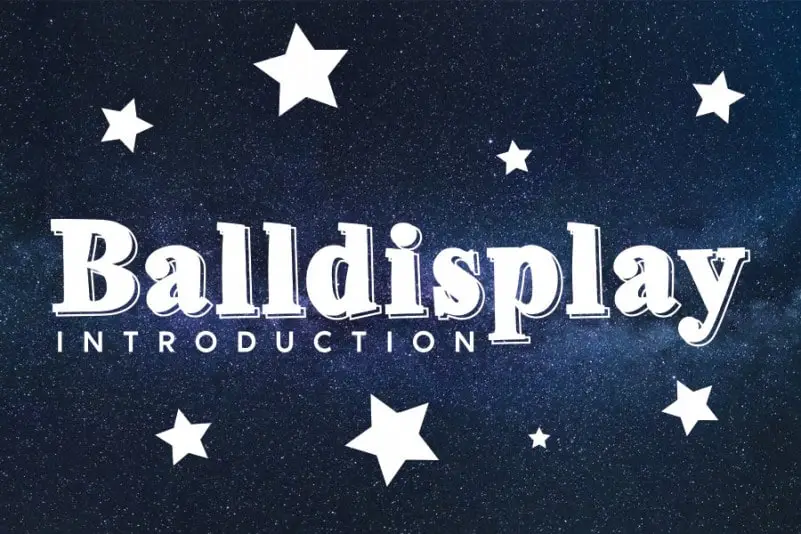
Balldisplay Display Font
A Balldisplay Display Font é uma elegante combinação de estilo serif que traz vivacidade para qualquer projeto visual. Com sua estrutura limpa e forte, esta fonte se destaca como a escolha perfeita tanto para logotipos quanto para projetos de marca, redes sociais ou até mesmo tarefas DIY criativas. Ideal para quem busca uma mistura suave de elegância e personalidade em suas produções digitais, seja ela de grande dimensão nos logotipos ou de menor escala nas mensagens diárias. A sua usabilidade se encaixa perfeitamente com a diversidade de ideias que o mundo do design pode oferecer, garantindo um toque único e alegre para qualquer projeto.